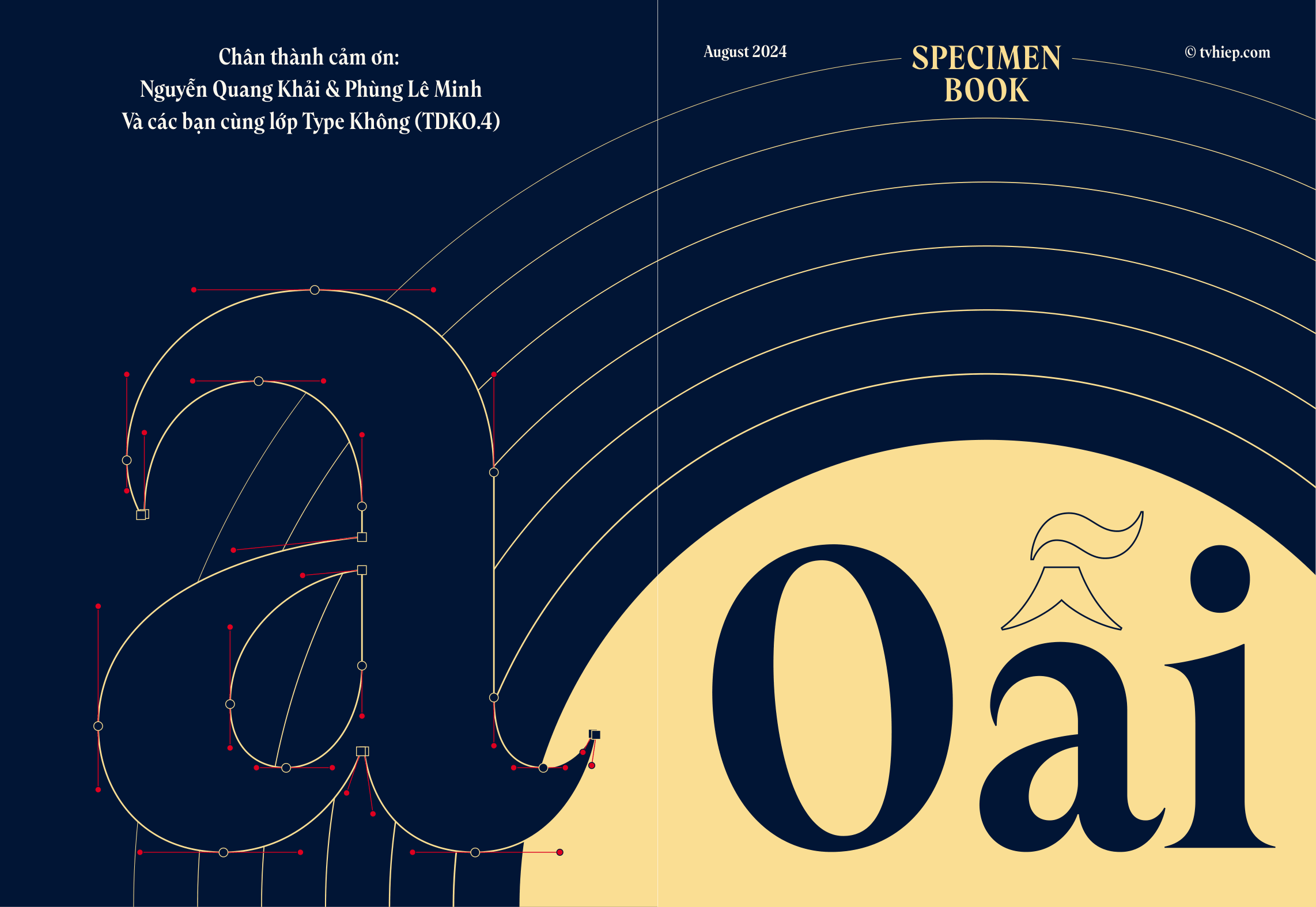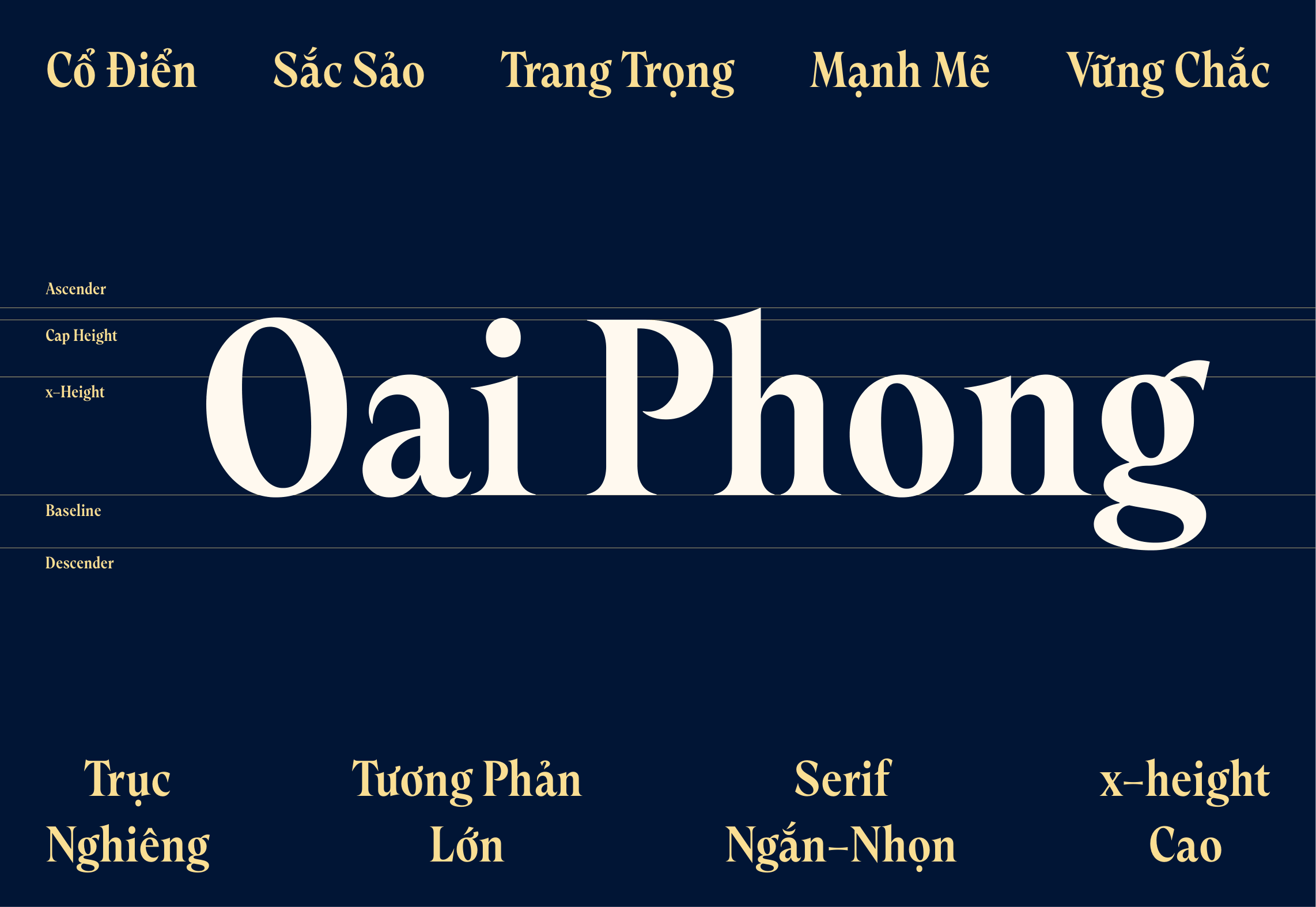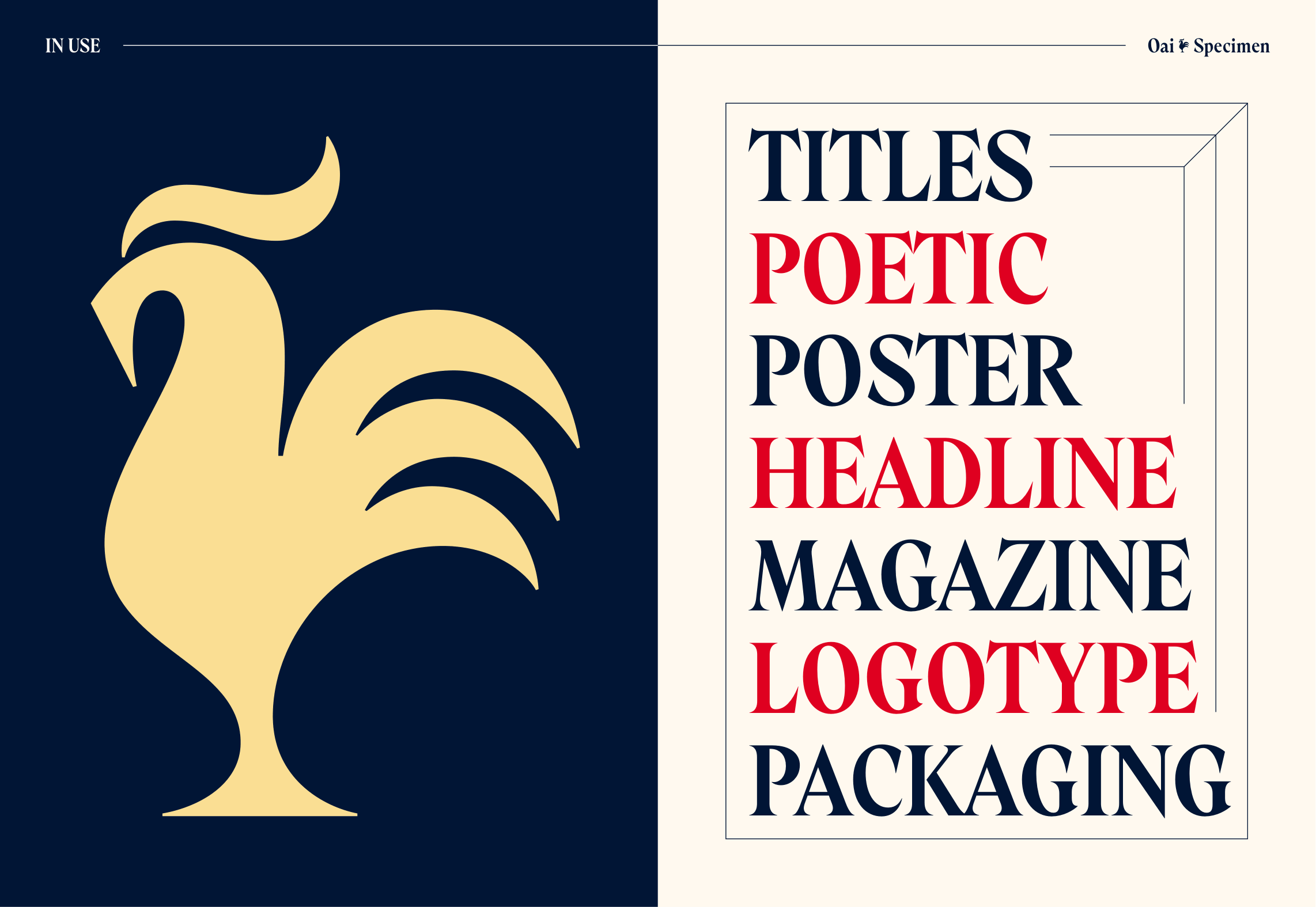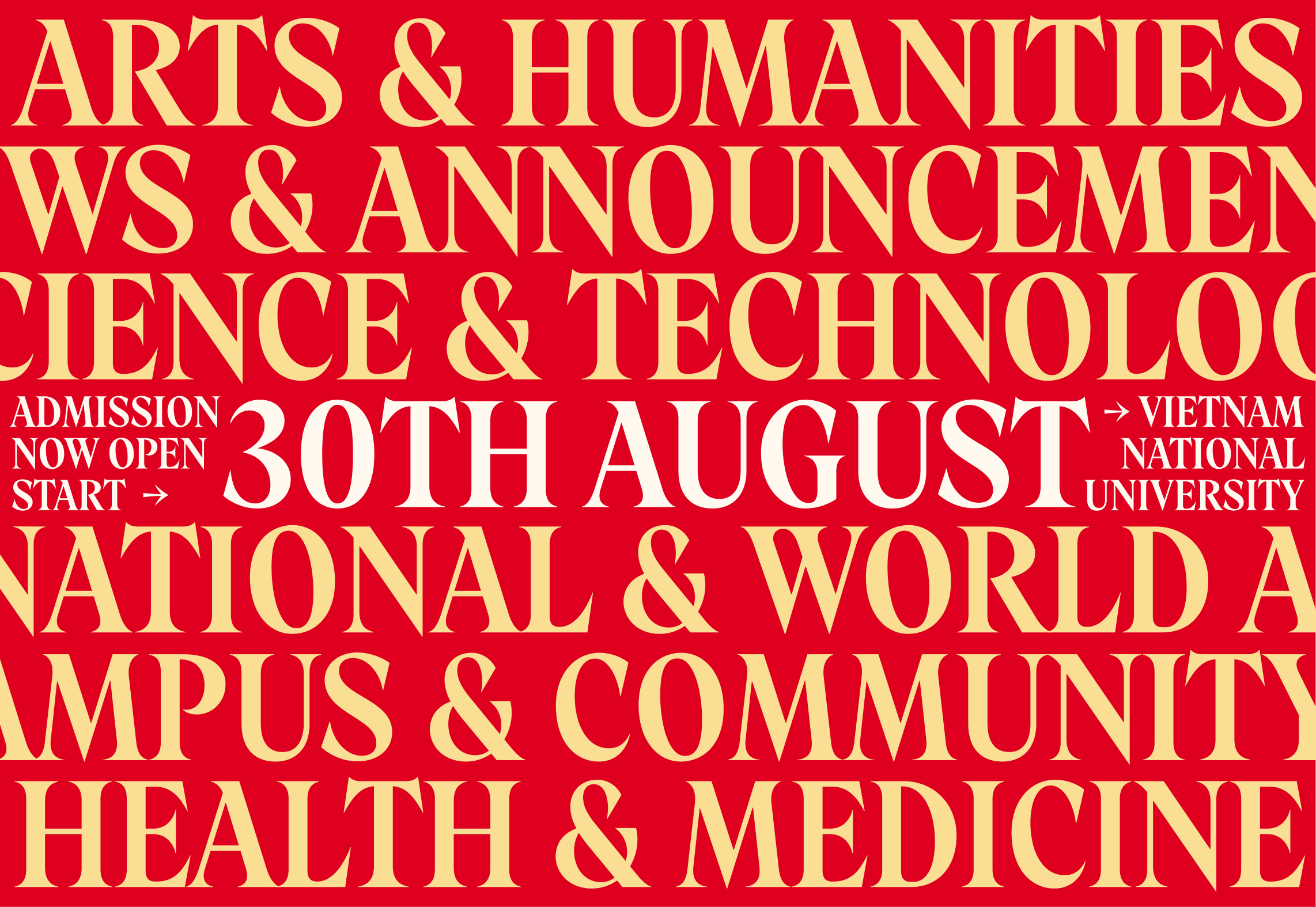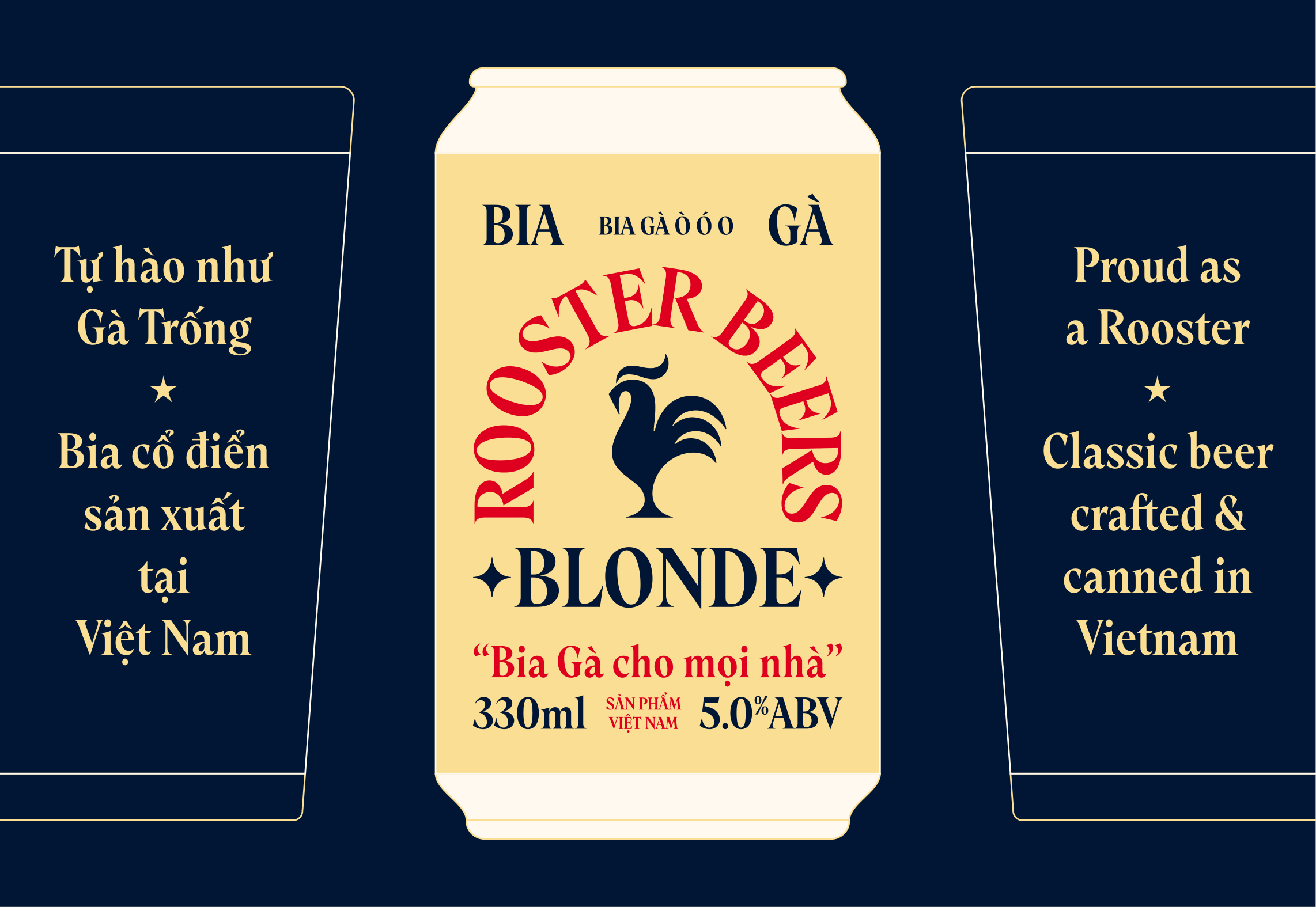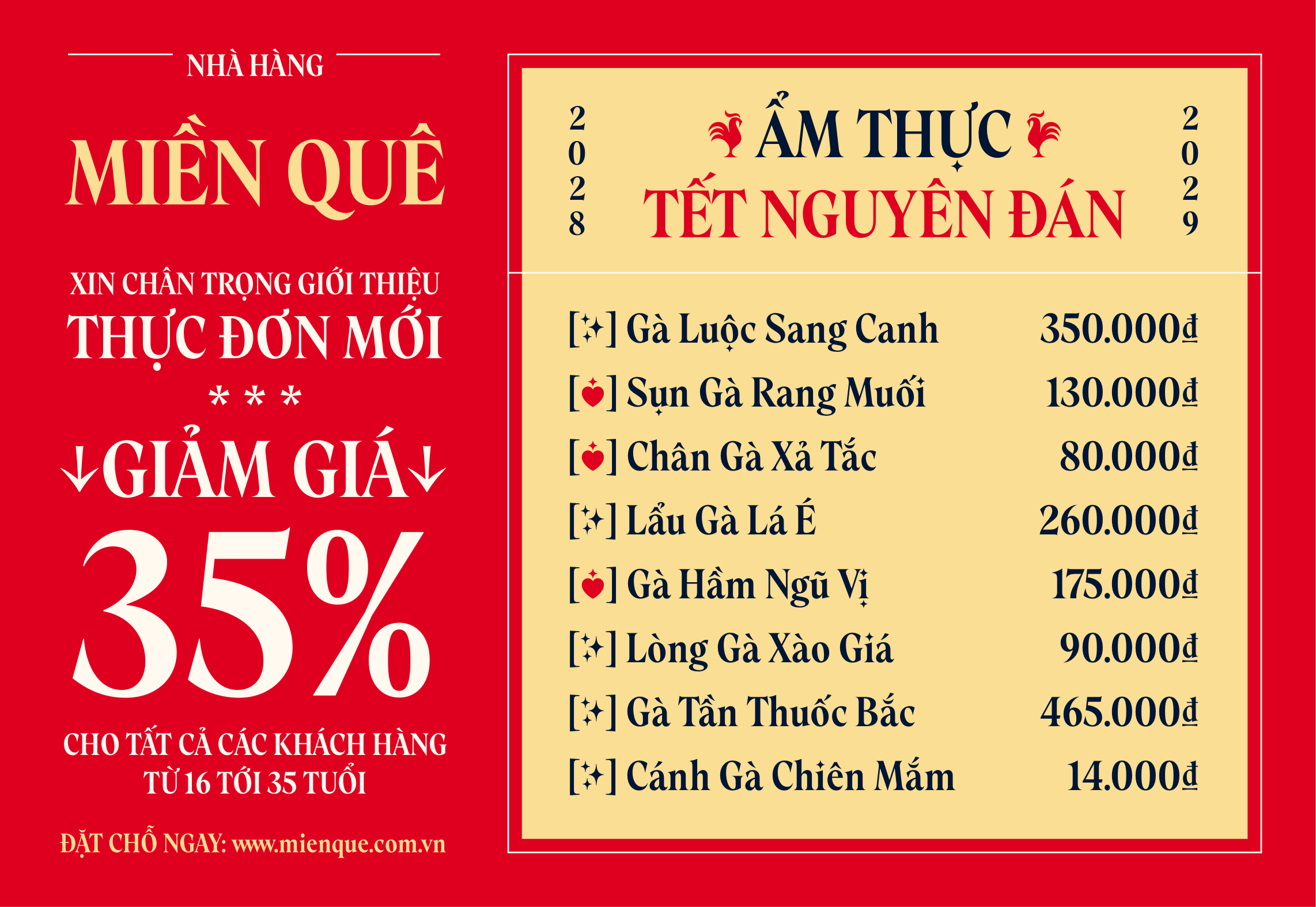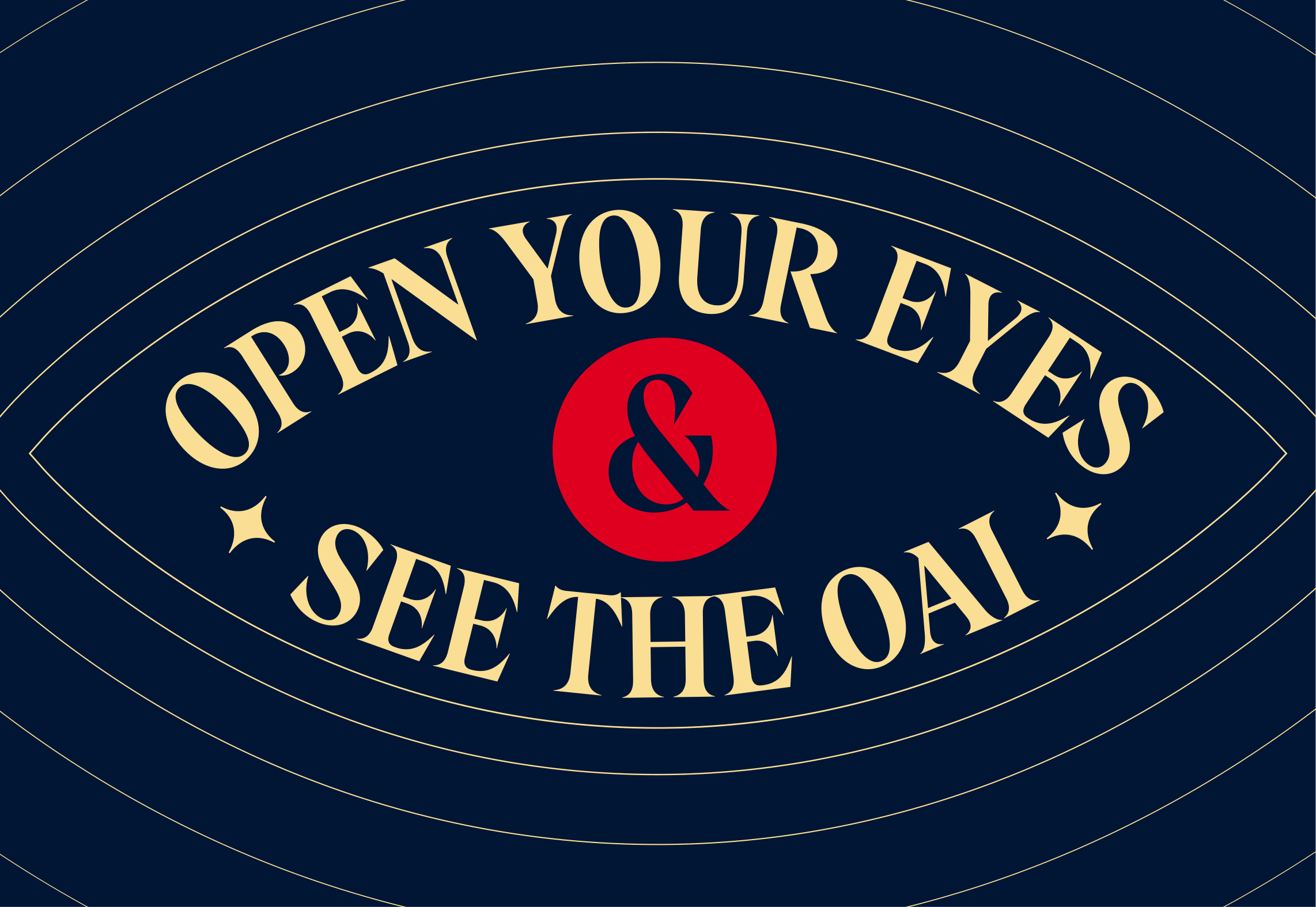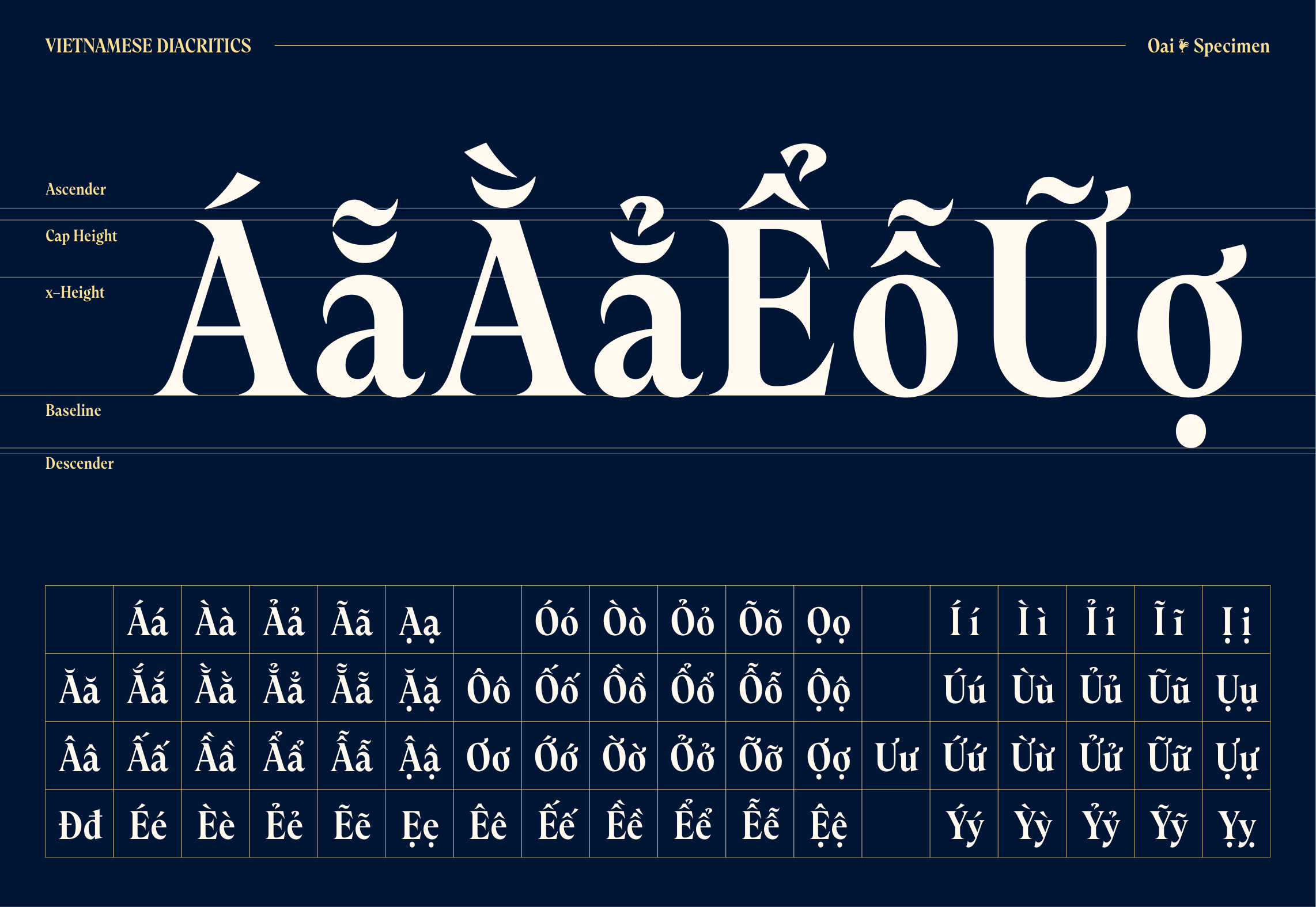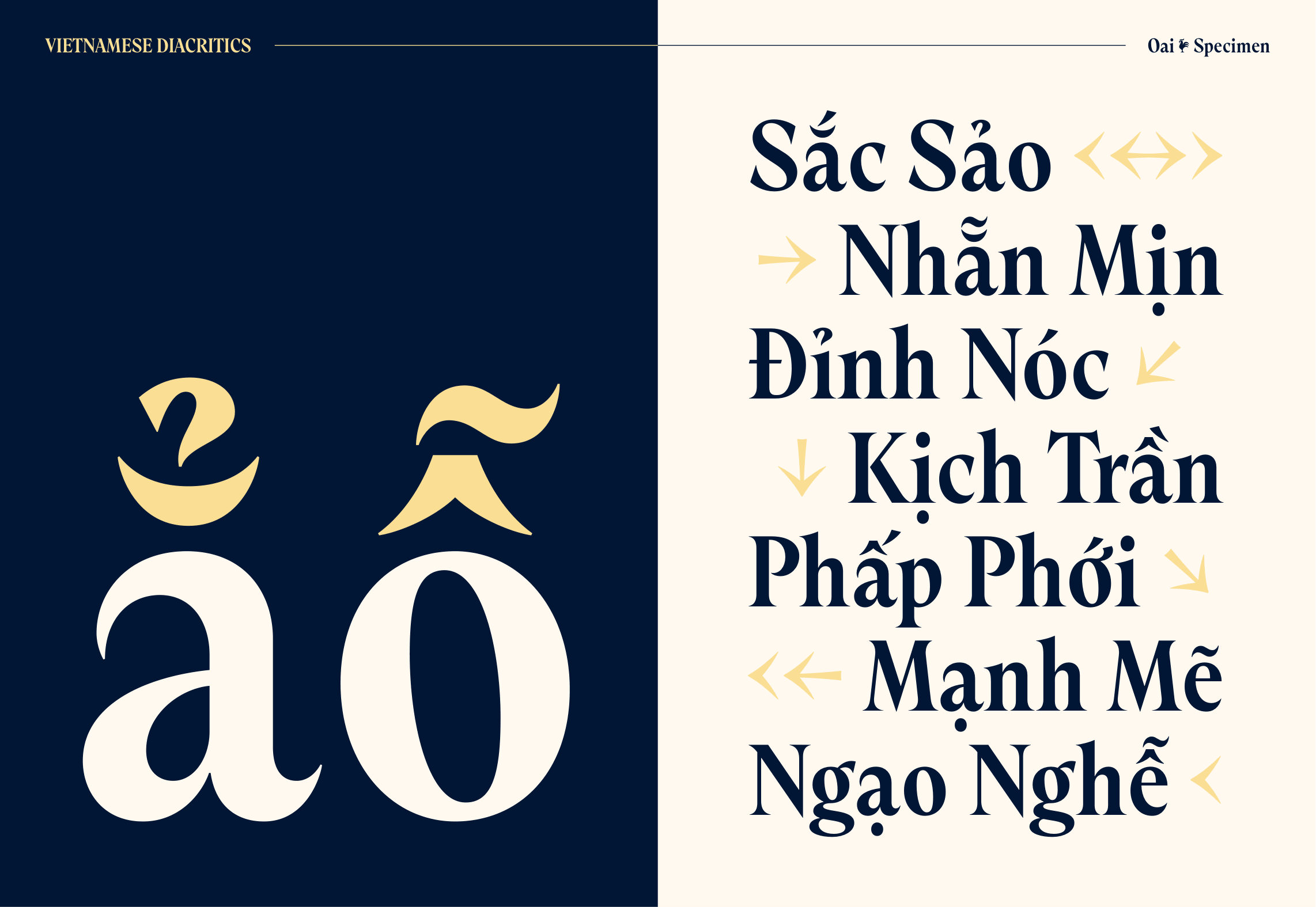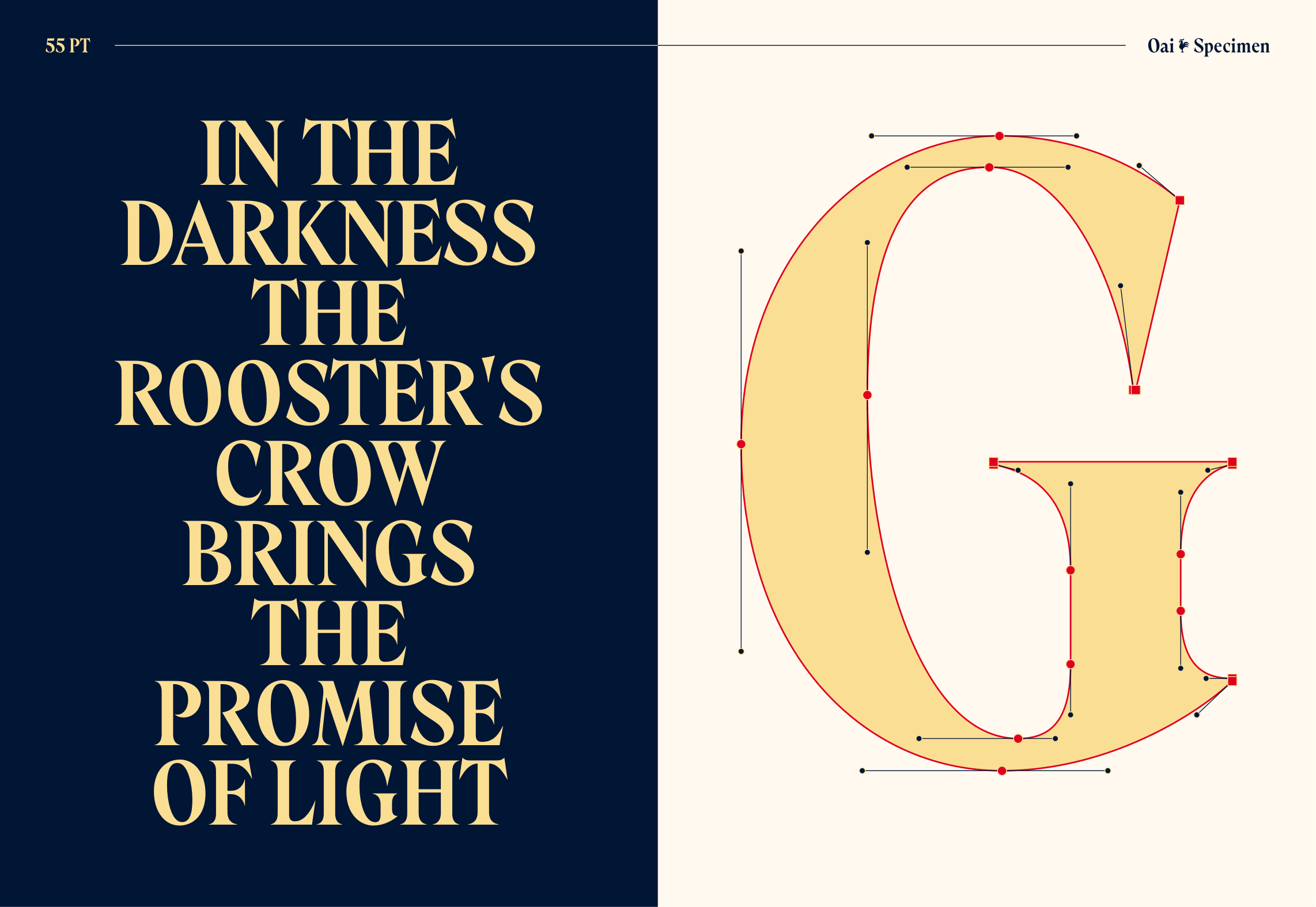
TVH Oai Display
Về TVH Oai Display: OAI là kiểu chữ serif display mang tinh thần humanist, lấy cảm hứng từ Laureate — một kiểu chữ được phát triển bởi Keystone Type Foundry tại Philadelphia vào năm 1901. Nổi bật với thiết kế serif loe, chắc khỏe cùng độ mở không gian âm lớn, Laureate chủ yếu được sử dụng cho tiêu đề và các dòng chữ lớn.
Laureate Bold is a robust, flared sans-serif typeface with characteristically short extenders, a design born out of the bold display typography needs of American printing at the turn of the 20th century.
The Keystone Type Foundry was established in Philadelphia in 1888, originally operating out of 734 Sansom Street as the Mather Manufacturing Company under the N.W. Ayer & Co. advertising agency. It grew into one of the most prolific independent American foundries of its era before being absorbed into the giant trust. In 1917, the foundry was purchased by American Type Founders, and Laureate, along with the rest of Keystone's catalog, passed into ATF's hands.